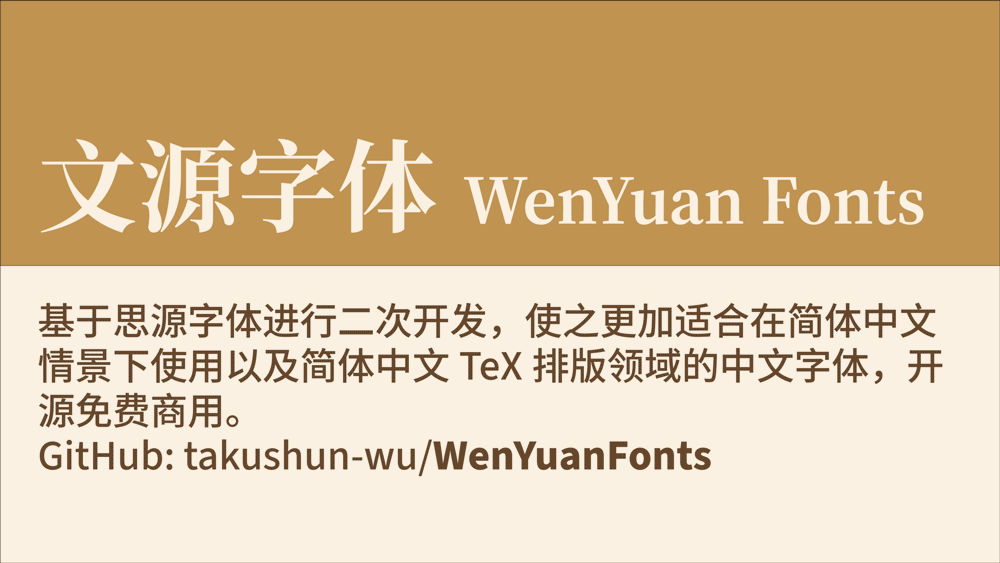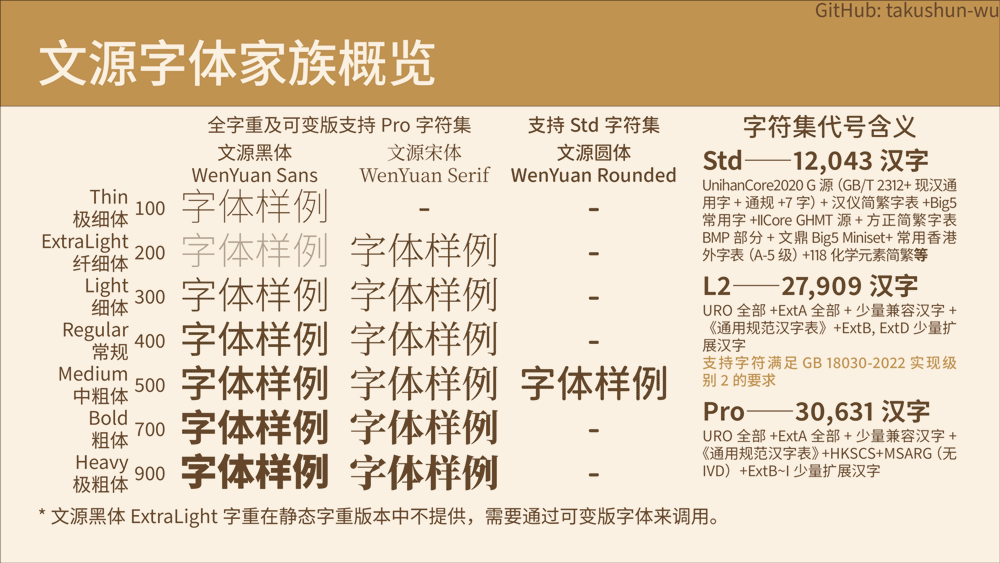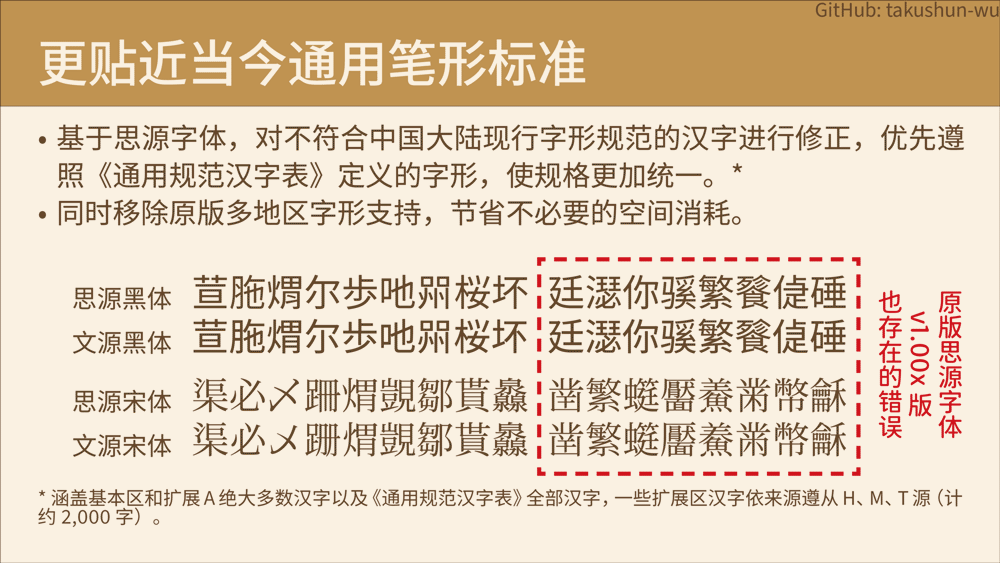
文源宋体(WenYuan Serif)是基于思源宋体二次开发的一款开源免费商用字体,主要是为了优化简体中文情景及TeX排版。
由于原版的思源宋体要同时支持中国大陆、港台、日韩等多个地区的字形,导致部分地区版本可能出现字形不符合当地标准。所以文源字体针对这些弊病做了优化,比如改正原版错误汉字字形、移除多地区字形支持、减少字体空间占用以及增加西文字符、拉丁文斜体等,甚至还在此基础上新增了一个文源圆体(后面也会介绍到)。